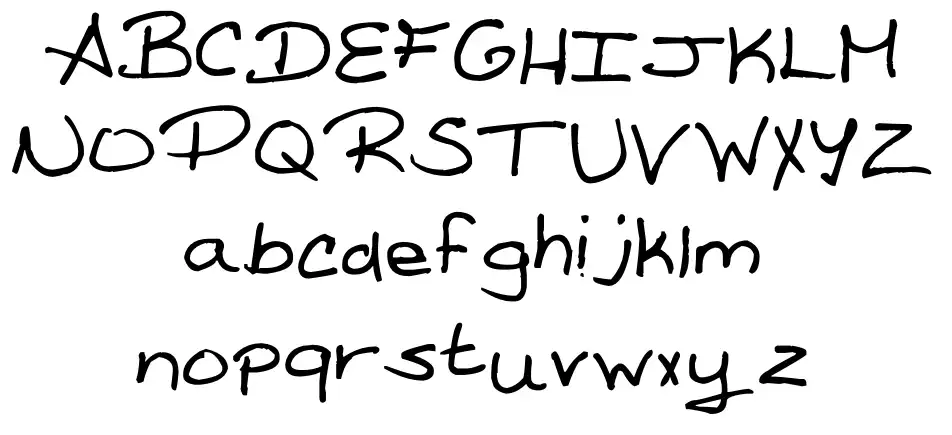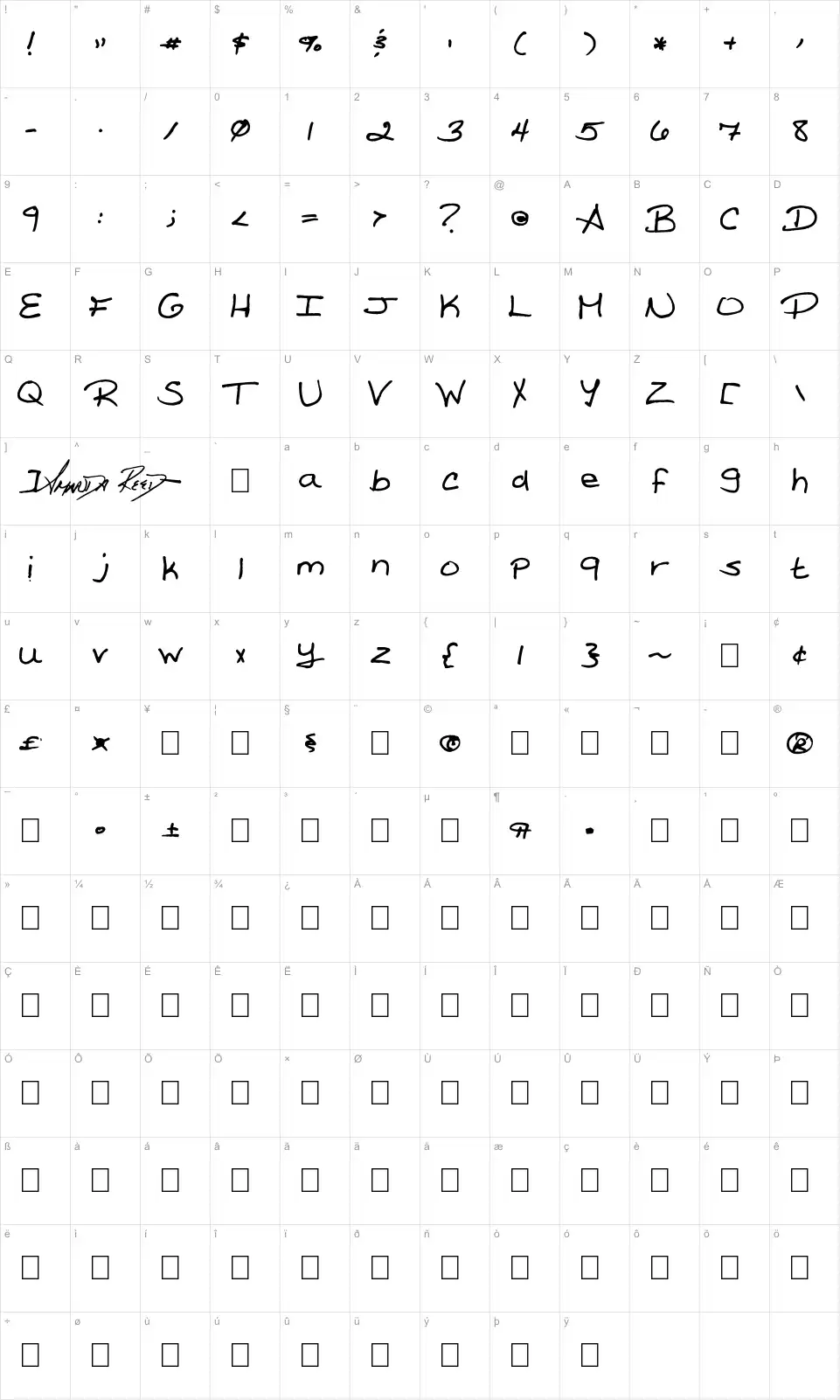
A Amanda Reed’s Font é uma fonte script de escrita manual criada pela Reed’s Writing. Se você está procurando por esta fonte, é uma ótima escolha para adicionar um toque de elegância a suas criações digitais. Com uma categoria de script e escrita manuscrita, a Amanda Reed’s Font é perfeita para usar em designs pessoais, letras de vídeo ou qualquer projeto onde você queira incorporar um estilo elegante e sofisticado. Quem utiliza esta fonte adquire a licença gratuita, disponível apenas em formato TTF. Ela foi adicionada em 12 de julho de 2022 e já foi baixada por 3247 pessoas. Com um tamanho de 13 KB, é uma opção compacta e eficiente para incorporar à sua coleção de fontes. Descarregue agora e veja como a Amanda Reed’s Font pode tornar suas criações digitais um pouco mais especial.
Designer: Reed’s Writing